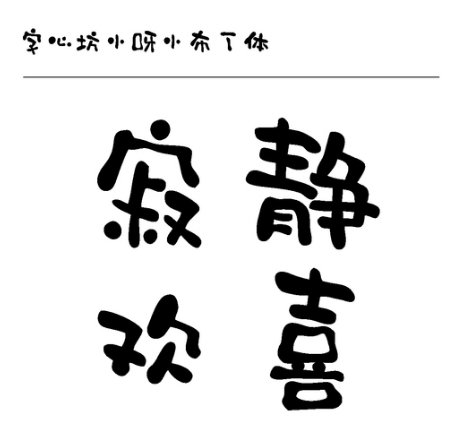
字心坊小呀小布丁是官方最新上線的一款卡通字體,造型采用了可愛的布丁特色,筆畫圓溜溜的仿佛要跳動起來,給人十分活潑生動的視覺體驗!
該字體由以為古靈精怪的魔法少女創(chuàng)作而成,前期書寫過程充分的反映創(chuàng)作者心靈對于美好意境的詮釋,后經(jīng)電臺設(shè)計軟件進行去雜、修正、編輯,最后做成計算機字庫。
字體風(fēng)格新穎、可愛、個性、小清新、時尚、有趣!
小呀小布丁字體有著清新童稚般的體驗好感,讓你的內(nèi)容變得更加憨厚可愛,兼具藝術(shù)字體和pop字體的風(fēng)格,讓你的包裝設(shè)計、品牌設(shè)計更吸引大家的眼光。